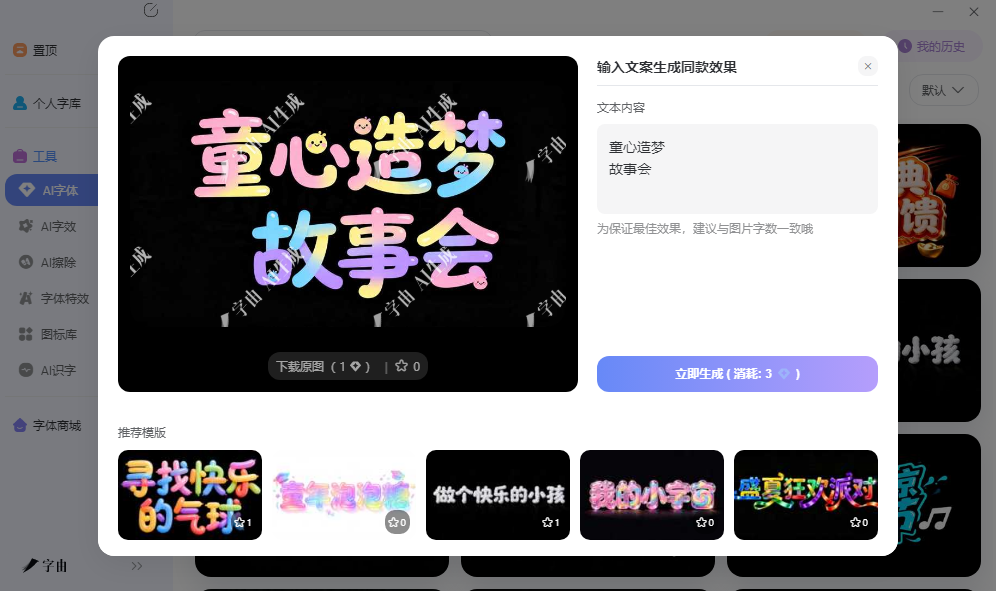
艺术字免费生成资源,海报封面快速出方案
做海报或者封面时,标题字往往是视觉焦点,但很多人不会用Photoshop,也不想为了几个字专门去学设计软件。其实现在有不少工具可以直接生成带特效的艺术字图片,保存后拖进海报模板或者PPT里就能用。这篇文章整理了五个艺术字免费生成渠道,从中文场景到英文特效都有,帮你快速出方案。
字由的AI字体功能对做海报封面比较实用的一点是即开即用。打开网页版就能操作,不需要下载安装软件,临时在别的电脑上也能生成和下载。模板库里按使用场景做了细分,电商大促、新媒体封面、品牌海报、节日主题、国潮风格等方向都有独立分类。做春节海报直接点进节日分类找红色喜庆模板,做科技产品发布会就筛冷色调的发光效果,做文创品牌就选手写质感类,定位比较直观。
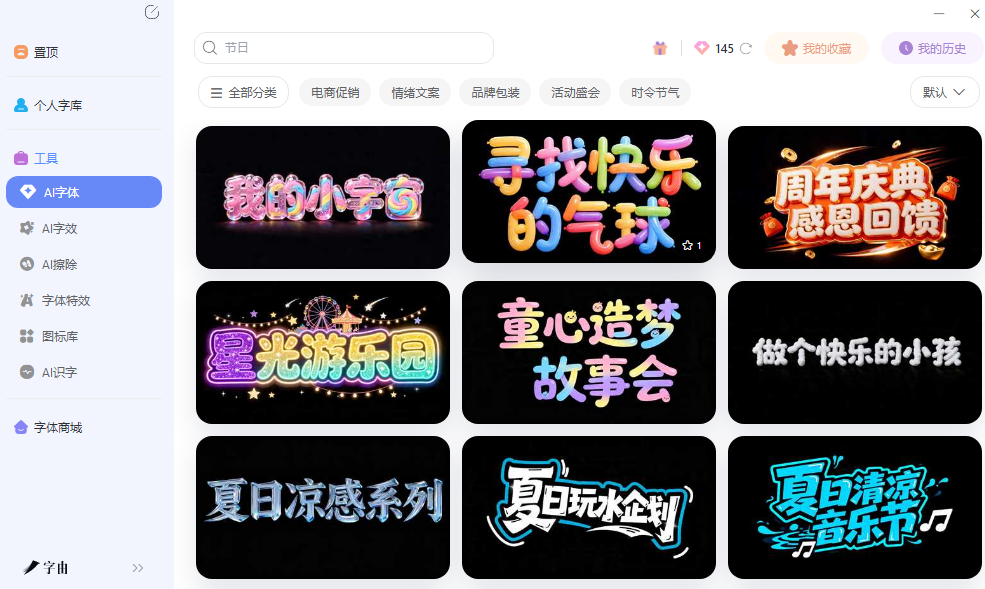
生成结果可以直接用在设计稿里。产出的是透明背景PNG,意味着能叠加在各种背景色或者底图上,不会留下白色方块。做公众号封面时,直接把生成的标题图拖进编辑器的封面区域;做活动海报时,拖进PS或者Canva里叠加在背景图层上;做PPT时,插入到幻灯片里调整位置即可。这种即拿即用的方式和传统设计软件里一层层调图层样式相比,省去了大量学习时间。
做海报封面不需要会专业设计软件,这篇文章说的就是这件事。字由的中文AI字体在场景细分和即开即用方面表现不错,配合每日免费额度,作为艺术字免费生成的主力渠道比较省心。TextPro的3D效果层次丰富,适合需要视觉冲击力的项目。Fast 3D Text在立体字的参数控制方面比较深入。Text Studio的自由度高,适合喜欢自己调配效果的用户。FontToPNG则胜在操作简单、输出直接。